排版是图形设计中最美丽,最令人沮丧的部分之一。正确使用字体会产生巨大的影响。不幸的是,事实恰恰相反。考虑到这一点,这是标准的最佳Photoshop字体。
选择合适的字体系列
在寻找合适的字体系列时-有很多可用的选项—您如何确定哪一个适合您? Adobe Photoshop随附各种在任何情况下都有用的内置字体,我们已尝试为您找到最适合的字体。
1。 Times New Roman
我们从Times New Roman开始。您是否在寻找易于阅读或不太浮华的字体?然后,Times New Roman是您最好的选择之一。它是最广泛使用的字体之一,Photoshop通过将其包含在程序中为我们提供了坚实的支持。
Times New Roman最初创建于1920年代,通常用于报纸,杂志上的正文文本。和书籍。它的可读性和跨数字程序的通用访问权限广受青睐。
2。 Baskerville
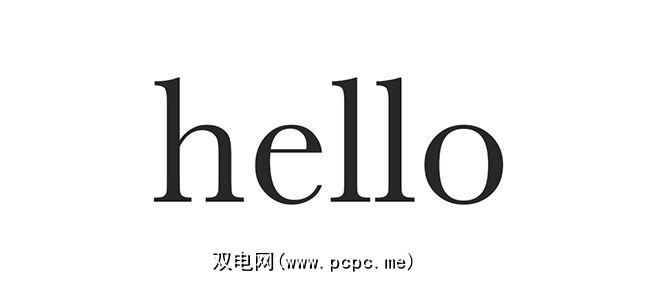
Photoshop随附的另一种“经典"字体是Baskerville:与Times New Roman相比,它是一种时尚,稍微“轻巧"的替代品,具有相同的易于阅读的功能和对空间的保守使用。应用时,它不会在页面上占据太多空间。
尽管Baskerville不如Times New Roman流行,但同样非常适合正文文本,并且可以用作标题的文本。较大范围内看起来不错。
3。美国打字机
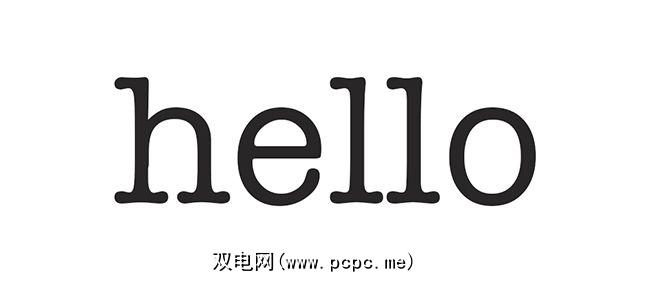
您是否正在寻找一种能与段落中的正文文本一起正常工作的平板衬线字体?您想要比Times New Roman更现代,更休闲的东西吗? American Typewriter是一个很好的答案,可以使您的文档具有“复古"外观。
4。爱德华七世时代脚本ITC
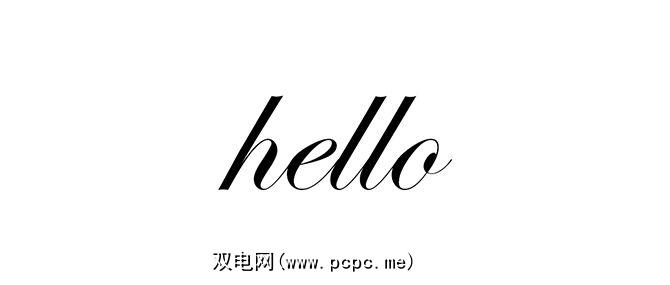
现在我们已经了解了基础知识,如果您想要一种看起来像草书的字体该怎么办?
Photoshop有两个,但其中一个最好的是爱德华七世时代的ITC:一种优雅,平衡的字体,在婚礼请柬,答谢卡和聚会邀请函上看起来都很不错。
但是,我们不建议您将此字体用于身体文字,因为它不如此列表中的其他文字清晰。
5。蒙特塞拉特(Montserrat)
当然,并非所有字体都具有“经典"外观,也不希望它们具有这种功能。
也许您正在寻找一种网络工具,在移动设备上看起来不错的友好字体,或者更接近当前设计趋势的字体。蒙特塞拉特(Montserrat)是此类中最有用的字体,其粗体,宽大的字体使其非常适合标题和标题。我已经在自己的网站上使用了多年。
一个警告词-这种字体不太适合正文。它的大尺寸意味着它是一个空间杀手。
6。 Century Gothic
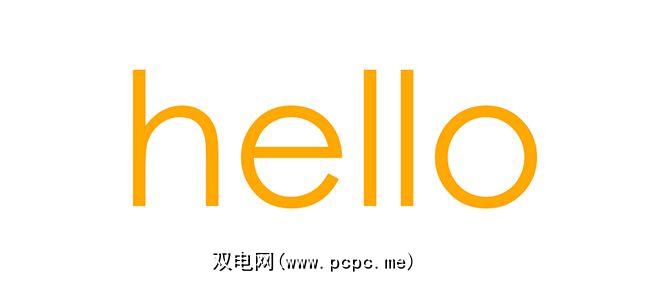
Century Gothic是无衬线字体,与Montserrat之类的字体相比,线条简洁,线条轻巧。您可以将其用于标题和标题,如果小心的话,也可以用于简短的段落。但请注意,如果这些段落过长,世纪哥特式字体将使它们难以阅读。
7。 Helvetica
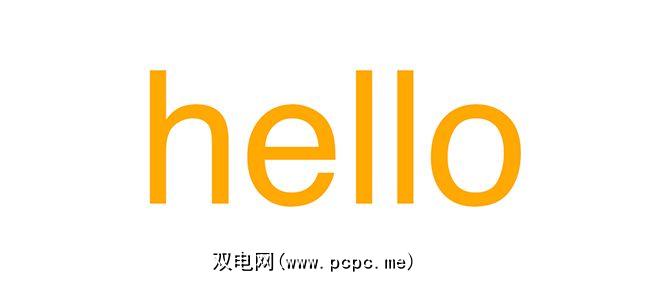
很难选择最好的字体,因为字体太多了。其中一些也取决于个人品味。但是,如果您要寻找一种适用于几乎所有设计的简单,现代的字体-从专业报告到旅行手册,那么最好与Helvetica搭配使用。
Helvetica是一种受到广泛赞誉的字体因其多功能性和易读性。
8。它很好地适用于标题,标题和正文,而且字母之间的间距非常漂亮,一旦应用,就很难弄乱您的设计。 8。磷酸盐
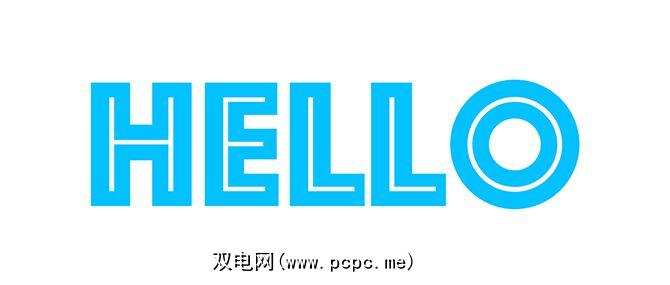
最好最后保存“ phun",对吗?我们知道,糟糕的双关语,但是有时候您想要一个活泼的字体来做广告。 Photoshop附带的最佳选项之一是Phosphate,它是一种大胆的宽字体,非常适合海报上吸引眼球的标题。由于它的大小,我们不建议在正文中使用它,但是它非常适合标题。
9。包豪斯93
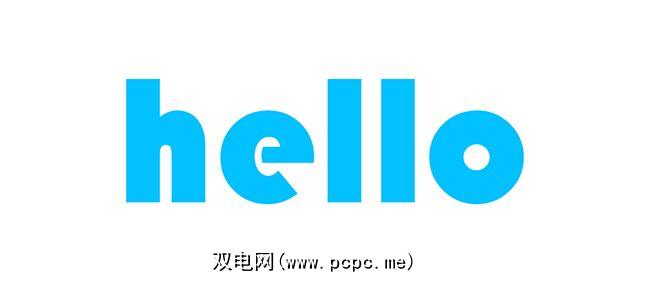
是否正在寻找一种装饰性字体,它比磷酸盐泡沫更气泡,更友好,更古怪?包豪斯93号将达到目的。像它较重的邻居一样,该字体又大又粗,最适合用于海报和小册子的标题。
10。 Braggadocio
最后但并非最不重要的是,Photoshop最好的San Serif设计之一是Braggadocio,这是一种大胆的,过分程式化的字体,需要立即引起注意。它适合采用复古设计的标题,但请谨慎使用。太多,它将使您的文本难以阅读。
最适合您的Photoshop字体是什么?
现在,您已经获得了Photoshop随附字体的简介。 ,您应该尝试一下它们,看看哪种适合您自己的个人喜好。
如前所述,设计可以是主观的,并且可能有些字体没有列入您认为是的列表中更适合您的文档。我们建议您仔细阅读所有内容,然后看看最适合您的方法。